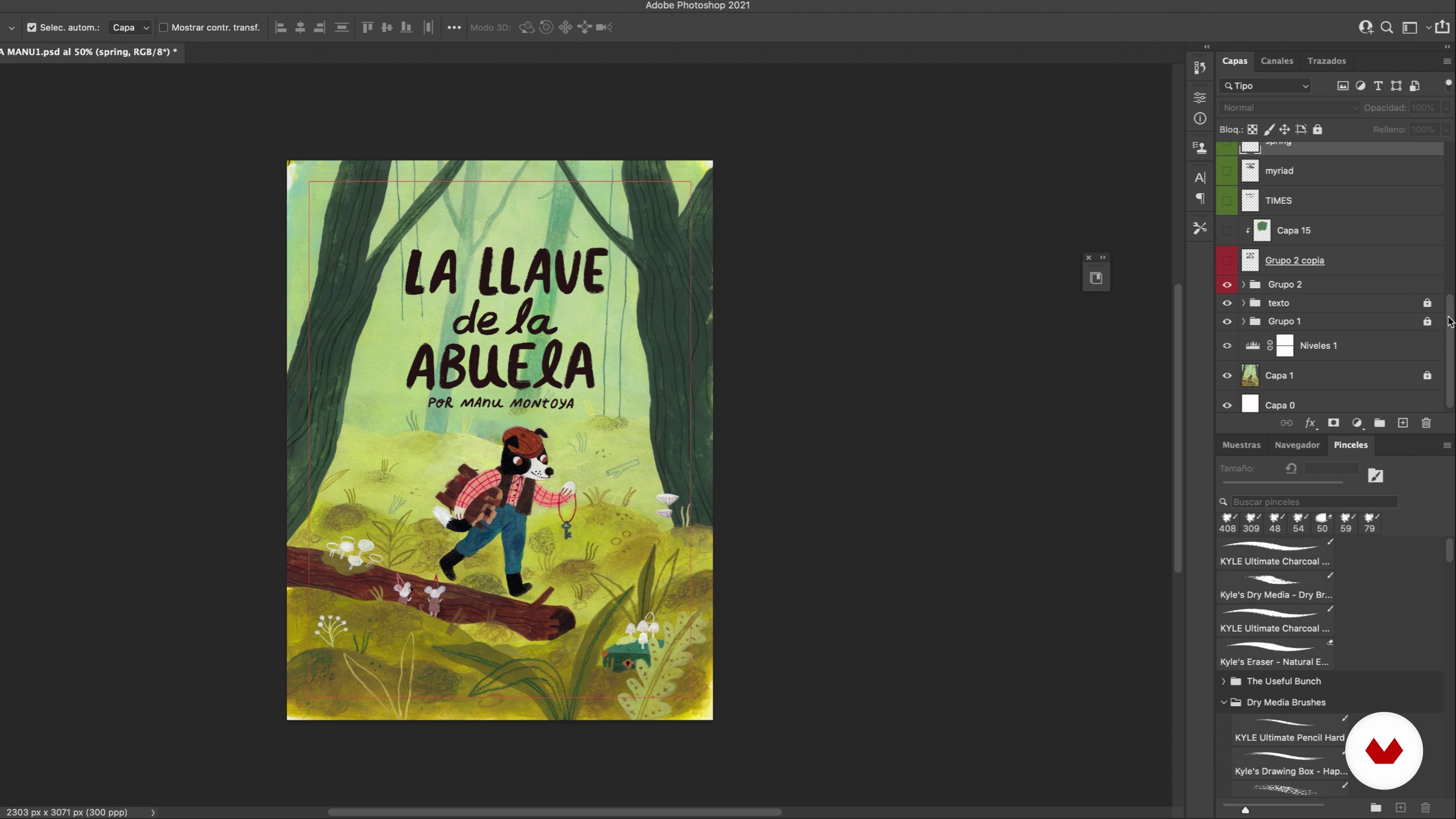
Título y elección de tipografía 2
“Prueba diferentes tipografías hasta que encuentres alguna que tenga relación con tu portada y genere armonía con la imagen. En esta lección, seguiré experimentando con el título y compartiendo lo que he aprendido sobre tipografías para portadas.”
“Título y elección de tipografía Con respecto al color, que es lo último en lo que pienso después de escribir y tener más o menos definido mi texto, tiene que haber un buen contraste entre el color de letra y el fondo. Este es un color complementario al del fondo. Al fondo tengo un verde y aquí tengo una especie de marrón tirando a rojo y muy oscuro, así que esto mejorará mi legibilidad. Podría cambiarle el color. Y escoger a lo mejor un verde muy cálido a ver qué pasa. Aquí, por ejemplo, a lo mejor ya no lo veo tan bien. Tendría que esforzarme para leer el texto y lo que queremos es que el ...”